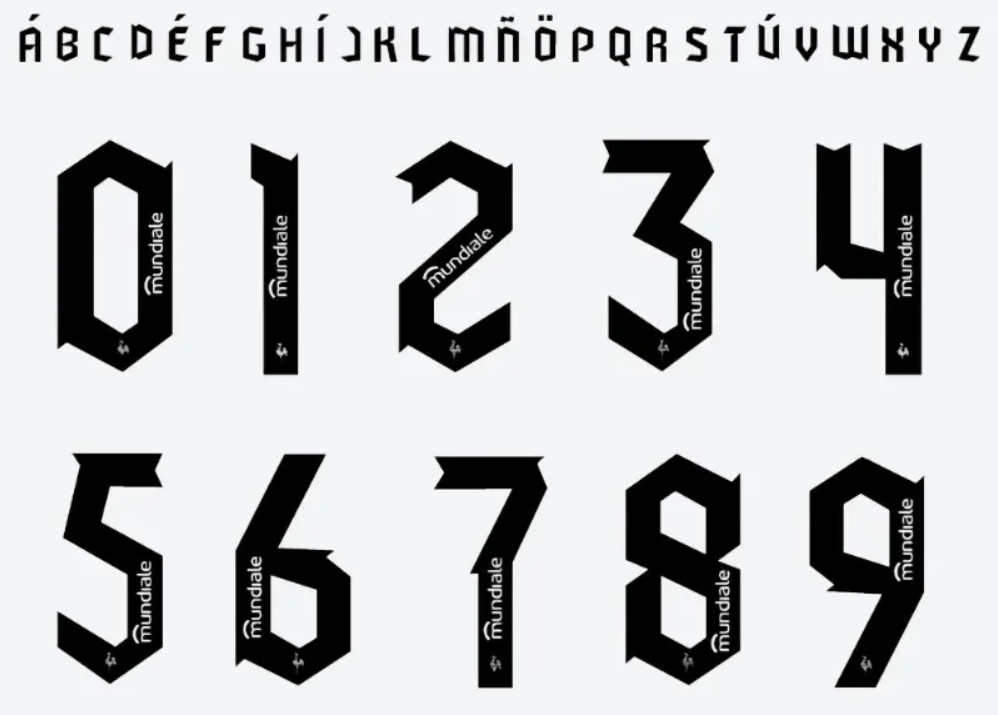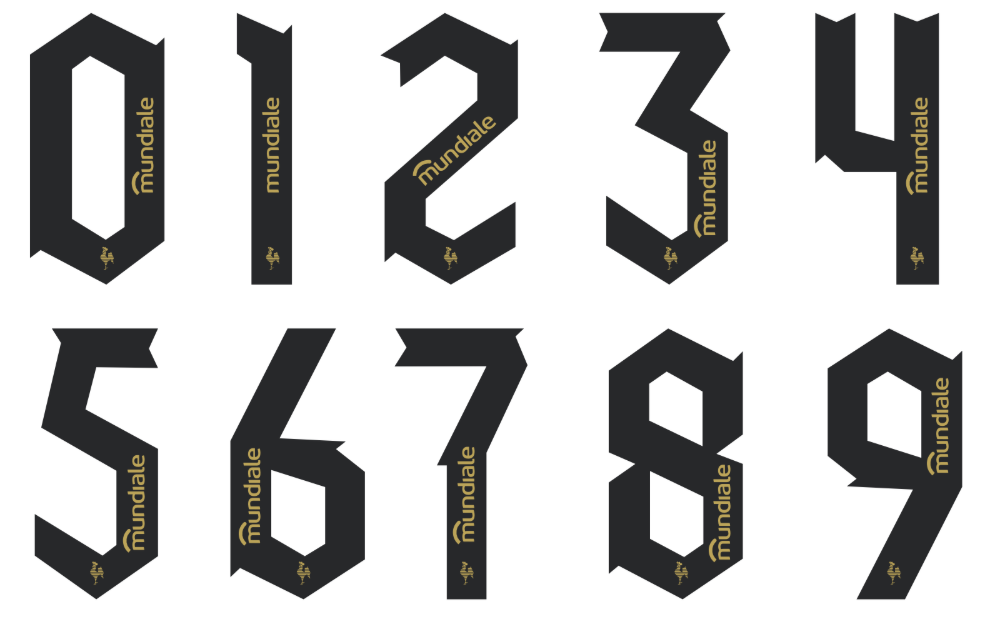
Fonte Atlético Mineiro 2025 Visitante: Baixe o TTF Oficial da Nova Camisa Adidas
A temporada 2025 chegou, e com ela os novos mantos que a Massa Atleticana tanto esperava. A Adidas, em parceria com o Galo, apresentou uniformes que misturam tradição e modernidade, e um dos detalhes mais procurados pelos designers é, sem dúvida, a nova tipografia.
A fonte utilizada no uniforme visitante (Away Kit) do Atlético Mineiro para 2025 é o destaque de hoje. Projetada para máxima legibilidade nos jogos fora de casa, esta é a fonte que estampa o nome e os números dos craques do Galo. Se você busca replicar essa identidade visual em seus projetos, chegou ao lugar certo.
Detalhes Técnicos da Fonte
• Nome da Fonte: Atlético Mineiro 2025 (Visitante)
Estilo e Identidade Visual
Desenvolvida pela Adidas, a fonte do uniforme visitante 2025 do Atlético Mineiro foca em clareza e impacto. Ela apresenta um design robusto, com cantos levemente arredondados e um toque geométrico, garantindo que os números e nomes sejam perfeitamente visíveis mesmo em movimento. É uma tipografia que transmite força e seriedade, características que definem o Galo em campo, destacando-se com elegância no uniforme predominantemente mais claro.